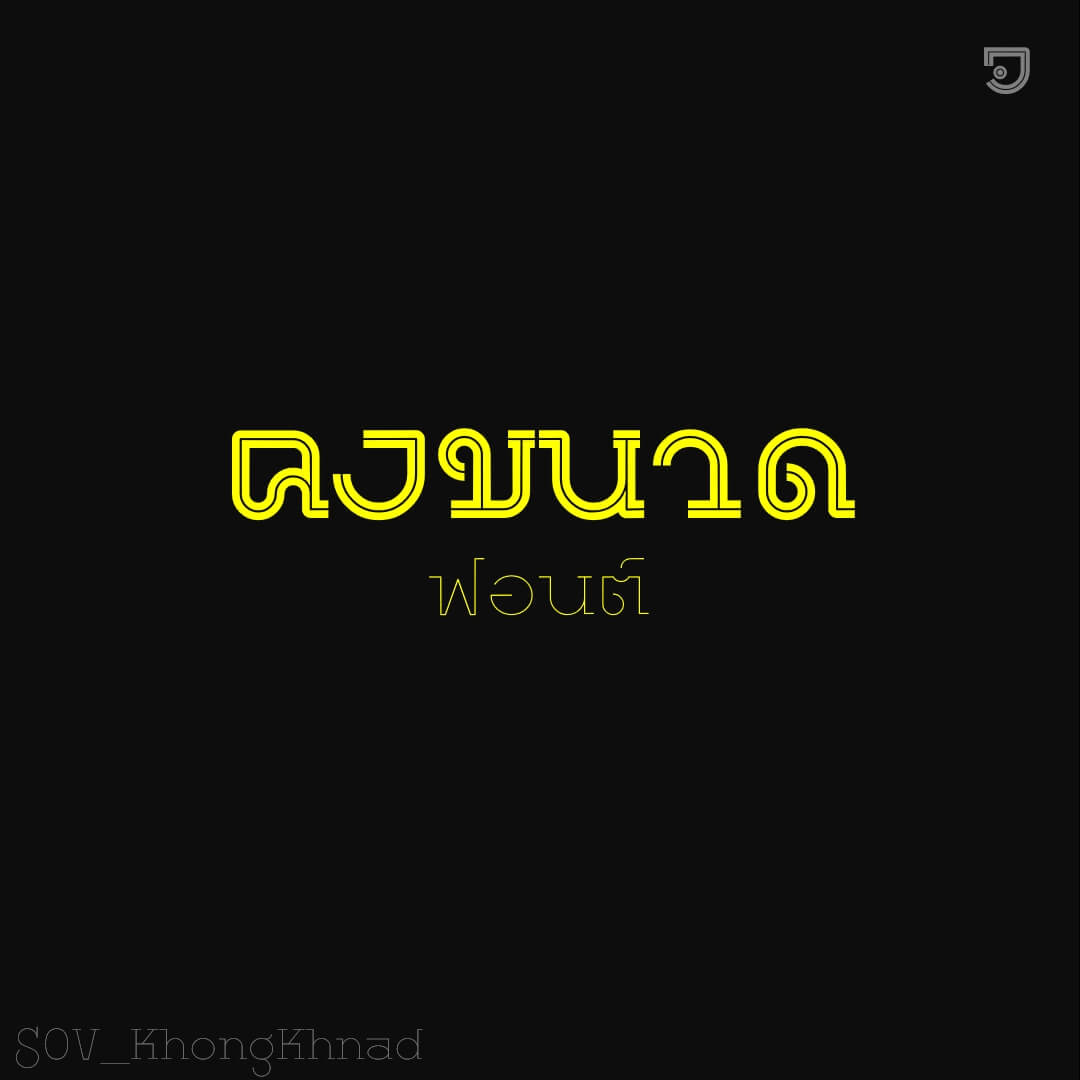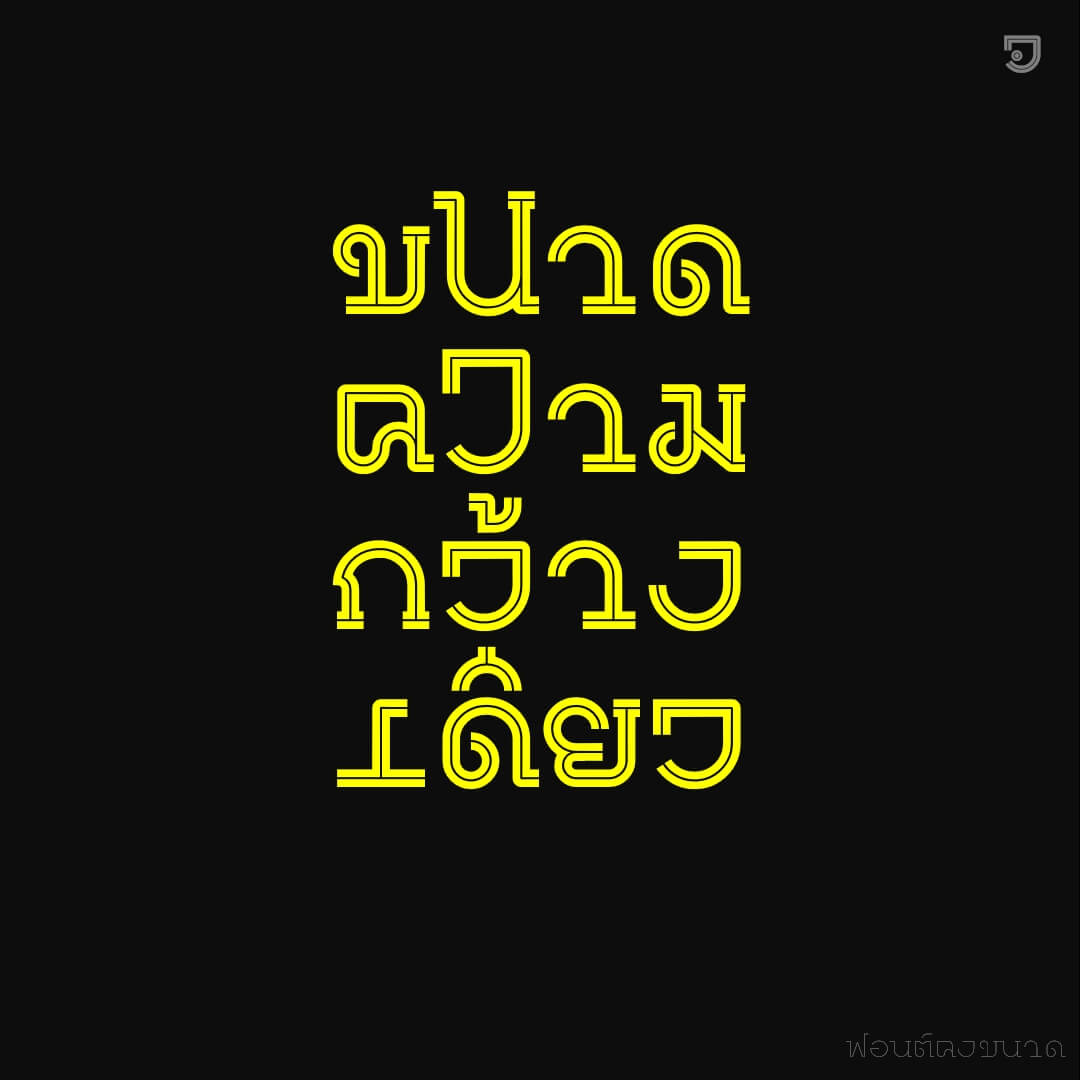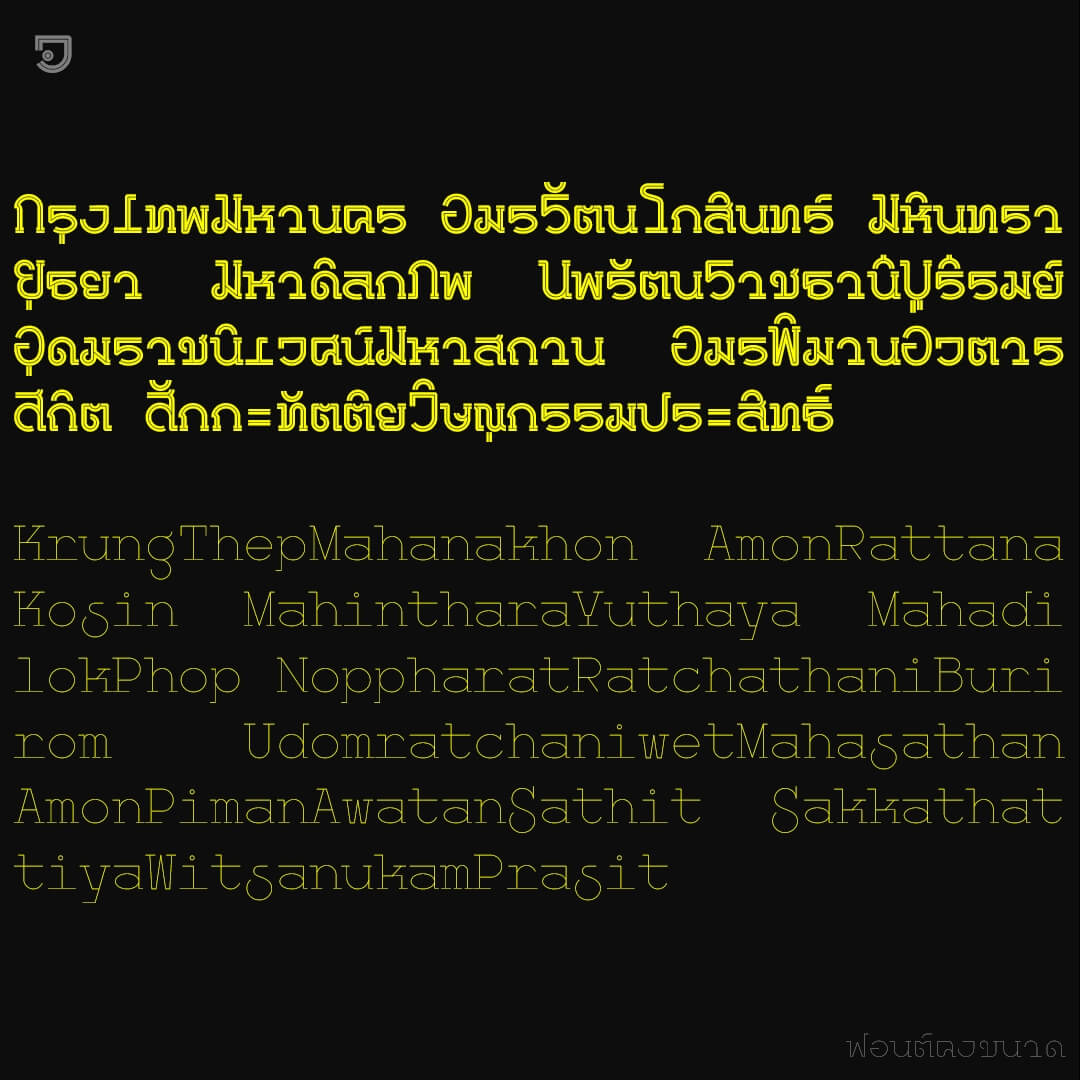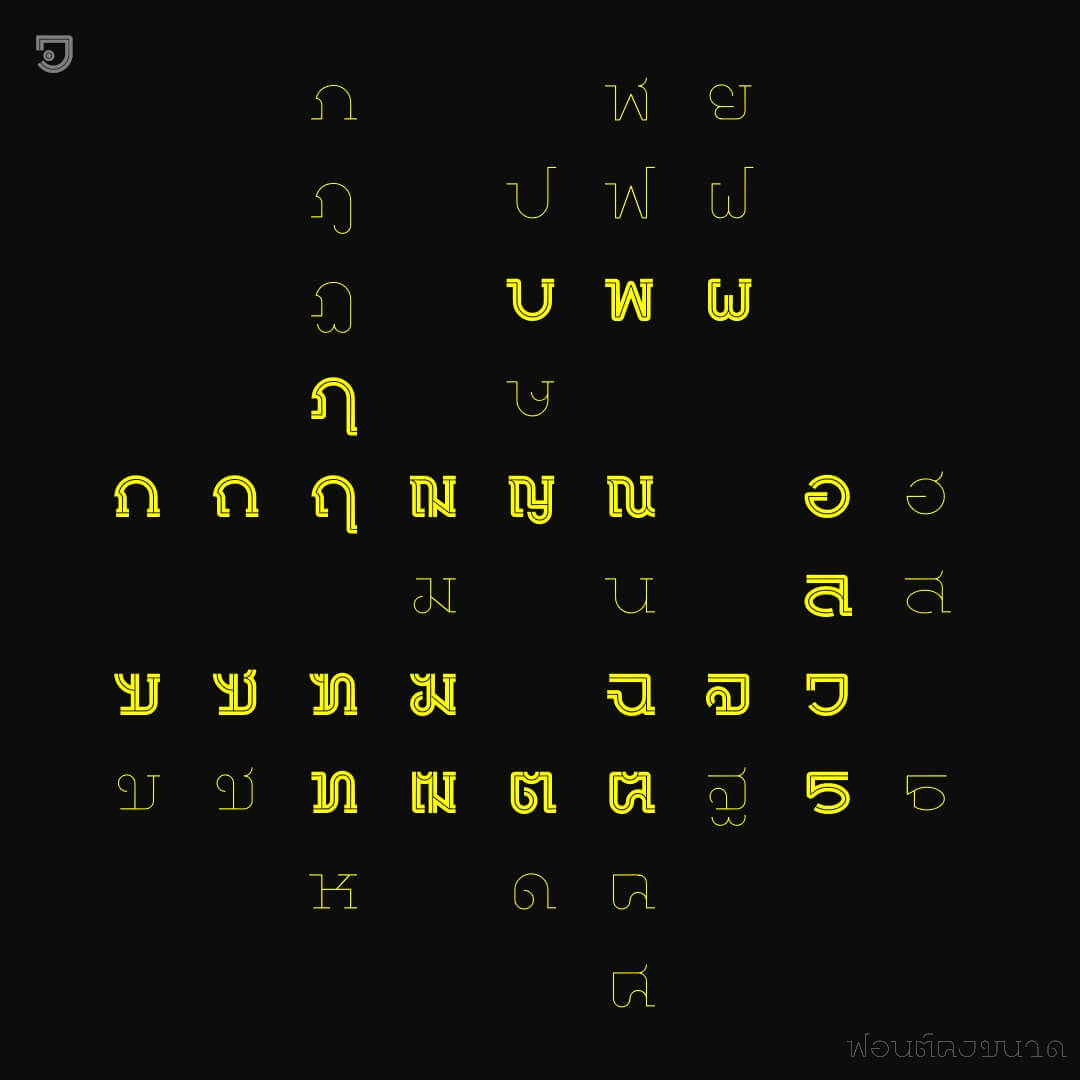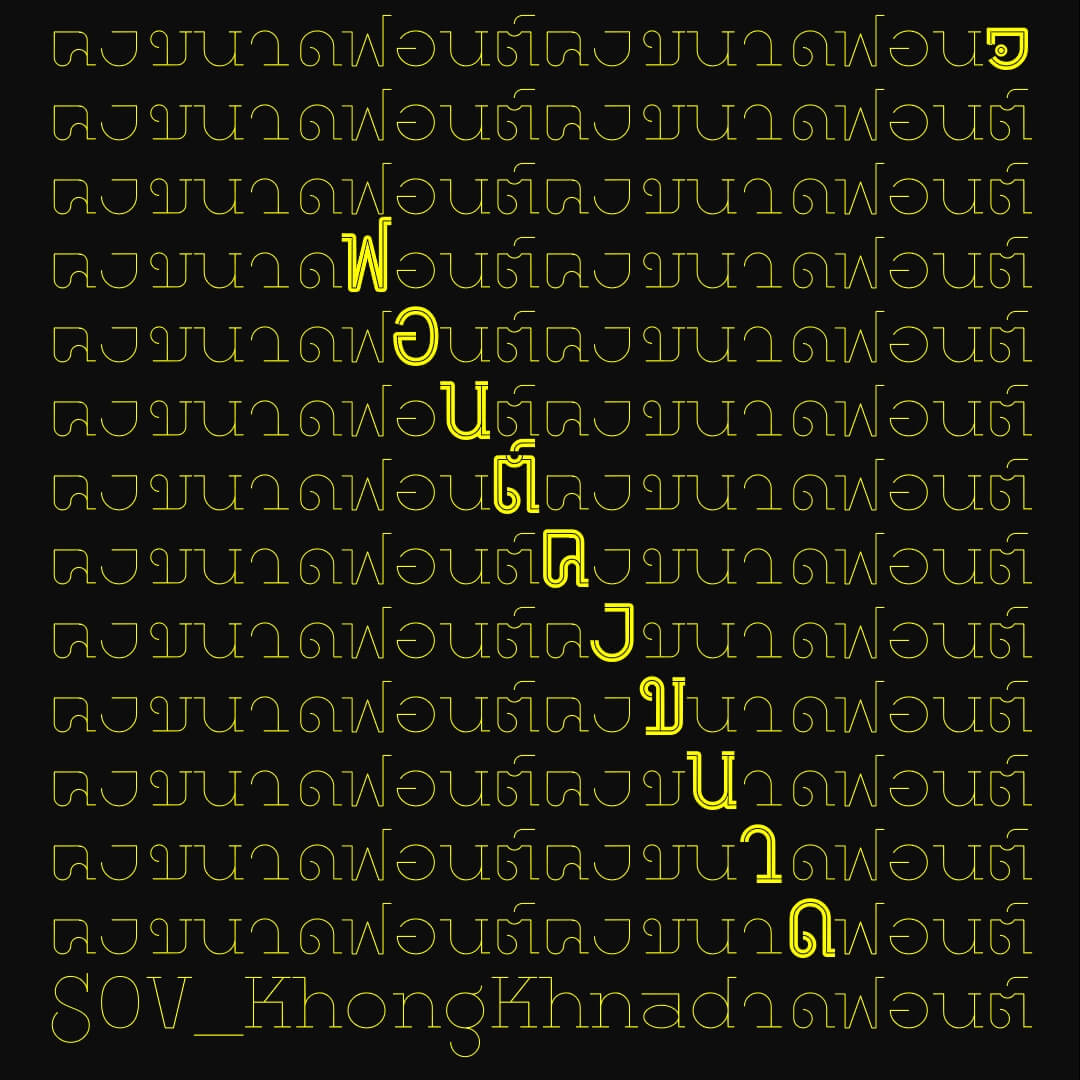
คงขนาด (SOV_KhongKhnad)
ฟอนต์คงขนาด – เป็น monospace font ขนาดกว้างเท่ากันทุกตัวอักษร มี 2 น้ำหนัก ตัวหนา 80 คว้านไส้ตรงกลาง ส่วน ตัวบาง หนา 10 กว้างเท่ากันทั้ง 2 น้ำหนัก เพิ่มตัวพิเศษสูงเท่า Capital letter ส่วน สระบน 2 ชั้น จะลดขนาดให้ไม่สูงกว่า Capital letter
เบื้องหลังการออกแบบ : ฟอนต์ คงขนาด
ฟอนต์ : คงขนาด (SOV_KhongKhnad)